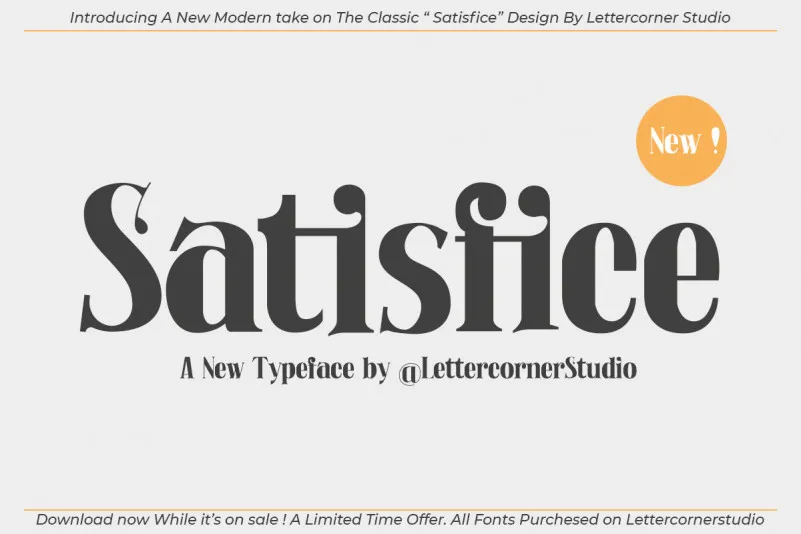
Satisfice Font – Download Grátis
A Satisfice Font é uma fonte serif gratuita criada pelo Studio Lettercorner, disponível para uso livre. Esta elegante fonte seria perfeita para aplicações variadas como logos, branding empresarial, design web, cartões de visita, embalagens de produtos e muito mais. Seja você um designer iniciante ou profissional, esta fonte oferece um toque de sofisticação que certamente enriquecerá seu próximo projeto. Seu estilo serif acentua seus textos, tornando-as uma escolha conveniente para design gráfico, desde logotipos até materiais impressos em cartões de visita ou embalagens comerciais. Inspirado na estética do século XIX, você terá um elemento visual elegante que certamente destacará seu trabalho. Satisfice Font é mais do que uma fonte, ela é a paixão de quem cria belas soluções visuais e gráficas.